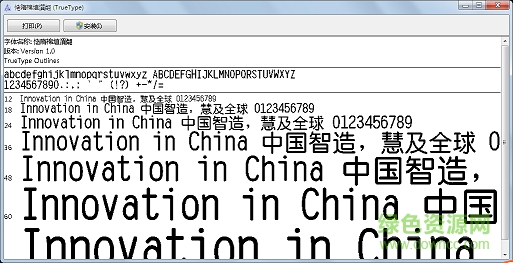
gbyenround bold字體又叫文鼎粗圓簡(jiǎn)體,是一款豐圓柔潤(rùn)的文鼎字體,字形飽滿(mǎn)端正,打印效果清晰,表現(xiàn)力強(qiáng),喜歡的小伙伴快來(lái)綠色資源網(wǎng)下載吧!
gbyenround bold字體是一款圓腳邊中粗的中文簡(jiǎn)體字,經(jīng)常被用于欄目制作中的標(biāo)題,大字報(bào)中很常見(jiàn)。